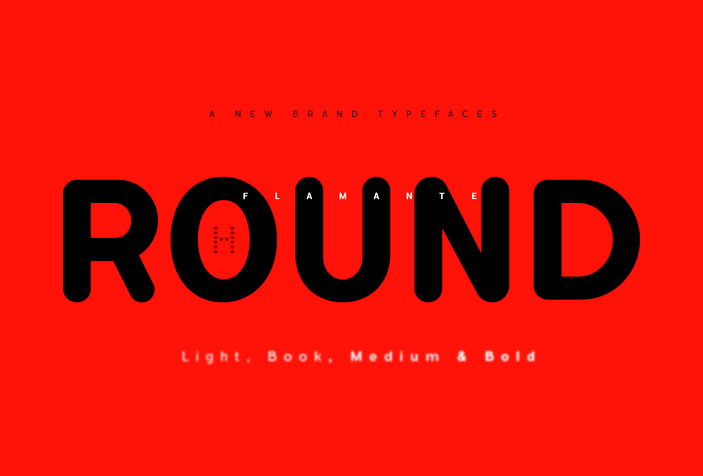
A Flanante Round é uma coleção de fontes para uso empresarial que combina geometria pura com delicadas curvas, criando um estilo neo-grotesco e arredondado. Este grupo de oito tipografias foi concebido para garantir excelente leitura tanto em títulos quanto em textos curtinhos ou aplicações de sinalização. Os pesos Light, Book, Medium e Bold, juntamente com suas respectivas itálicas, fornecem uma ampla gama de opções para designers e empresas. A Flanante Round é ideal para ambientes que valorizam modernidade e funcionalidade, oferecendo um equilíbrio entre simplicidade geométrica e leveza arredondada, perfeita tanto para uso em grandes títulos quanto para textos mais discretos. Esta fonte se destaca como uma opção clara e elegante para estilos de marca que desejam expressar confiança sem perder a personalidade. Com um design sofisticado que combina facilidade de leitura com modernidade, a Flanante Round é perfeita tanto para uso em aplicativos digitais quanto em materiais impressos. Com uma mistura exuberante de geometria e delicadeza arredondada, a Flanante Round se destaca como uma escolha inteligente para aqueles que procuram um equilíbrio entre simplicidade e beleza na tipografia.